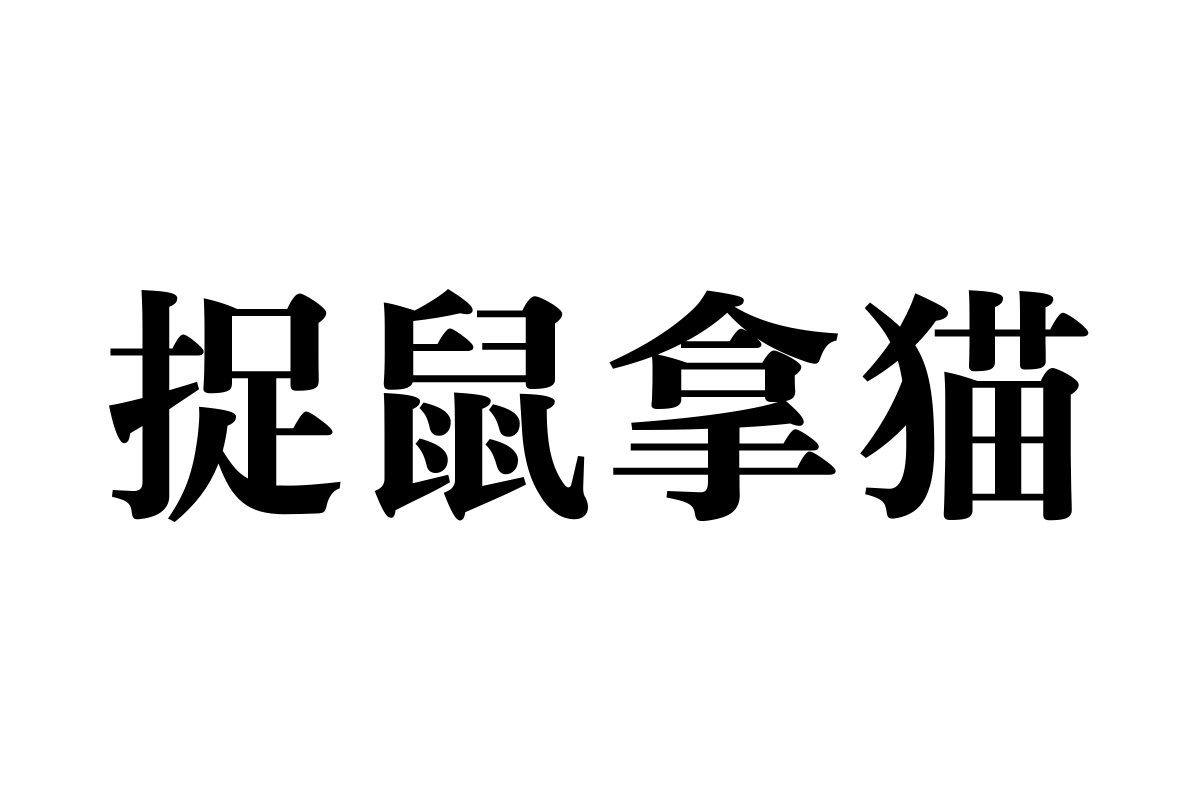
汉仪玄宋75S是一款现代简约风格的中文字体,具有独特的艺术风格和强烈的视觉冲击力。这款字体采用了简洁的线条勾勒出文字的形状,使得整体看起来更加清晰、易读。同时,它又不失优雅和时尚感,能够很好地融入各种设计场景中。
汉仪玄宋75S字体的特点在于其流畅的笔画和优美的字形。它的笔画粗细适中,既有力量感又不失柔和,给人一种轻松愉悦的感觉。在字形上,这款字体呈现出一种独特的美感,仿佛是在描绘一幅美丽的画卷。无论是用于标题、正文还是装饰性的文字,都能够展现出其独特的魅力。
此外,汉仪玄宋75S字体还具有一定的可塑性。设计师可以根据需要对其进行个性化的调整和组合,以适应不同的应用场景和设计风格。这使得这款字体成为了设计师们展现创意和个性的有力工具。
总之,汉仪玄宋75S是一款现代简约风格的中文字体,具有独特的艺术风格和强烈的视觉冲击力。它不仅易于阅读,而且能够很好地融入各种设计场景中。如果您正在寻找一款适合您的项目需求的中文字体,那么汉仪玄宋75S绝对值得您考虑。